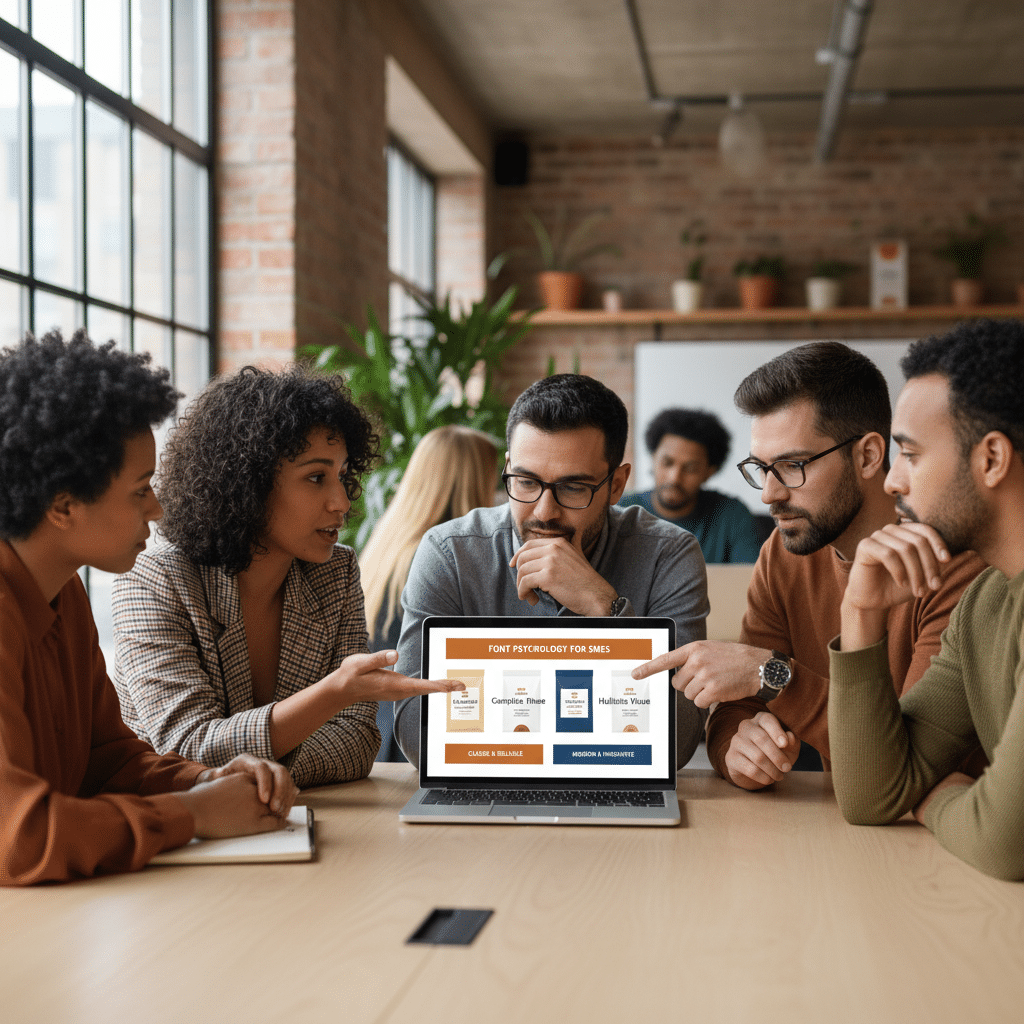
จิตวิทยาฟอนต์: เลือกฟอนต์ยังไงให้แบรนด์ดูน่าเชื่อถือ
การเลือกรูปแบบตัวอักษรหรือฟอนต์สำหรับแบรนด์นั้นมีความสำคัญมากกว่าแค่ความสวยงาม เพราะมันคือเครื่องมือสื่อสารที่ทรงพลังซึ่งทำงานในระดับจิตใต้สำนึกของลูกค้า ศาสตร์ที่ศึกษาเกี่ยวกับเรื่องนี้เรียกว่า จิตวิทยาฟอนต์: เลือกฟอนต์ยังไงให้แบรนด์ดูน่าเชื่อถือ ซึ่งเป็นแนวทางที่ช่วยให้ธุรกิจ โดยเฉพาะกลุ่ม SME สามารถสร้างภาพลักษณ์ที่แข็งแกร่งและน่าไว้วางใจผ่านการออกแบบอัตลักษณ์ของแบรนด์ เช่น โลโก้ ฉลากสินค้า หรือสื่อส่งเสริมการขายต่างๆ
ภาพรวมของจิตวิทยาฟอนต์
- จิตวิทยาฟอนต์ (Font Psychology) คือการศึกษาว่ารูปแบบตัวอักษรที่แตกต่างกันส่งผลต่อการรับรู้ อารมณ์ และพฤติกรรมของมนุษย์อย่างไร
- ฟอนต์ประเภท Serif (มีเชิง/มีหัว) มักสื่อถึงความดั้งเดิม ความน่าเชื่อถือ และความมั่นคง เหมาะสำหรับแบรนด์ที่ต้องการภาพลักษณ์ที่จริงจังและเป็นทางการ
- ฟอนต์ประเภท Sans-serif (ไม่มีเชิง/ไม่มีหัว) ให้ความรู้สึกทันสมัย เรียบง่าย และเข้าถึงง่าย เหมาะสำหรับแบรนด์ดิจิทัลและธุรกิจที่ต้องการสื่อสารความมั่นใจและเป็นมิตร
- การเลือกฟอนต์ที่เหมาะสมต้องคำนึงถึงบุคลิกของแบรนด์ กลุ่มเป้าหมาย และความสอดคล้องกับองค์ประกอบอื่นๆ เพื่อสร้างภาพลักษณ์ที่น่าเชื่อถือและเป็นที่จดจำ
- ความสม่ำเสมอในการใช้ฟอนต์ในทุกช่องทางการสื่อสารเป็นกุญแจสำคัญในการสร้างแบรนด์ที่แข็งแกร่งและน่าไว้วางใจ
ทำความเข้าใจ จิตวิทยาฟอนต์ คืออะไร?
จิตวิทยาฟอนต์ หรือ Font Psychology คือศาสตร์แขนงหนึ่งที่ศึกษาความสัมพันธ์ระหว่างลักษณะทางกายภาพของตัวอักษร (Typography) กับการตอบสนองทางอารมณ์และการรับรู้ของมนุษย์ ฟอนต์แต่ละแบบมี “บุคลิก” ที่แตกต่างกัน ซึ่งสามารถกระตุ้นความรู้สึกและความคิดที่หลากหลายในจิตใต้สำนึกของผู้ชมได้ทันทีที่มองเห็น ไม่ว่าจะเป็นความรู้สึกมั่นคง, ความทันสมัย, ความหรูหรา, หรือความเป็นมิตร สิ่งเหล่านี้เกิดขึ้นโดยอัตโนมัติและส่งผลโดยตรงต่อภาพลักษณ์ของแบรนด์
เมื่อลูกค้าเห็นฟอนต์ที่แบรนด์เลือกใช้ สมองจะประมวลผลและสร้างการเชื่อมโยงกับประสบการณ์หรือแนวคิดที่มีอยู่เดิม ตัวอย่างเช่น ฟอนต์ที่มีลักษณะคล้ายลายมือเขียนอาจทำให้รู้สึกถึงความเป็นส่วนตัวและความใส่ใจ ในขณะที่ฟอนต์ตัวหนาและแข็งแรงอาจสื่อถึงความกล้าหาญและความมั่นคง ดังนั้น การทำความเข้าใจในศาสตร์นี้จึงเป็นสิ่งจำเป็นสำหรับผู้ประกอบการและนักออกแบบที่ต้องการสร้างการสื่อสารที่มีประสิทธิภาพและตรงจุด
ฟอนต์ไม่ใช่แค่ตัวอักษร แต่คือ ‘เสียง’ ที่แบรนด์ใช้สื่อสารโดยไม่ต้องเอ่ยคำพูด มันสามารถกำหนดโทนและสร้างความประทับใจแรกพบที่ทรงพลังได้ในเสี้ยววินาที
ความสำคัญของฟอนต์ต่อการสร้างแบรนด์
ในโลกธุรกิจที่มีการแข่งขันสูง การสร้างความน่าเชื่อถือ (Trustworthiness) คือหัวใจสำคัญสู่ความสำเร็จ ฟอนต์มีบทบาทสำคัญอย่างยิ่งในการสร้างความไว้วางใจนี้ตั้งแต่แรกเห็น โดยเฉพาะอย่างยิ่งในธุรกิจที่ต้องการความมั่นคงสูง เช่น ธุรกิจการเงิน, บริการด้านสุขภาพ, หรือกฎหมาย การเลือกใช้ฟอนต์ที่ไม่เหมาะสมอาจสร้างความรู้สึกไม่เป็นมืออาชีพ, ไม่น่าไว้วางใจ และทำให้ลูกค้าเกิดความลังเลใจได้
ก่อนที่จะตัดสินใจเลือกฟอนต์ใดๆ แบรนด์ควรกำหนด “บุคลิก” ของตนเองให้ชัดเจนเสียก่อน เช่น แบรนด์ต้องการถูกมองว่าเป็นแบรนด์ที่จริงจังและน่าเชื่อถือ หรือเป็นแบรนด์ที่สนุกสนานและเป็นมิตร? เมื่อมีทิศทางที่ชัดเจนแล้ว การเลือกฟอนต์ที่สอดคล้องกับบุคลิกนั้นจะช่วยควบคุมการรับรู้ของลูกค้าและสร้างภาพลักษณ์ที่แข็งแกร่งและเป็นเอกภาพได้ ฟอนต์ที่เลือกอย่างมีกลยุทธ์จะกลายเป็นสินทรัพย์ที่สำคัญในการออกแบบโลโก้, บรรจุภัณฑ์, เว็บไซต์ และสื่อการตลาดทุกชนิด
หลักการสำคัญในการเลือกฟอนต์เพื่อสร้างความน่าเชื่อถือ
การเลือกฟอนต์ที่สามารถเสริมสร้างความน่าเชื่อถือให้กับแบรนด์ได้นั้นต้องอาศัยหลักการพิจารณาหลายประการ เพื่อให้แน่ใจว่าฟอนต์ที่เลือกไม่เพียงแต่สวยงาม แต่ยังสื่อสารคุณค่าและบุคลิกของแบรนด์ได้อย่างถูกต้อง
ความสอดคล้องกับบุคลิกแบรนด์ (Appropriateness)
ฟอนต์ที่เลือกต้องสอดคล้องกับยุคสมัย, บุคลิก, และค่านิยมหลักของแบรนด์ แบรนด์ที่ต้องการสื่อถึงความเป็นดั้งเดิมและความน่าเชื่อถือที่สืบทอดมายาวนาน อาจเลือกใช้ฟอนต์ประเภท Serif ที่ดูคลาสสิก ในทางกลับกัน แบรนด์เทคโนโลยีที่ต้องการสื่อถึงความทันสมัยและนวัตกรรม มักจะเลือกใช้ฟอนต์ Sans-serif ที่ดูสะอาดตาและเรียบง่าย การเลือกฟอนต์ที่ไม่เข้ากับบริบทของธุรกิจอาจสร้างความสับสนและลดทอนความน่าเชื่อถือลงได้
ความชัดเจนและอ่านง่าย (Readability)
นี่คือคุณสมบัติพื้นฐานที่สำคัญที่สุด ฟอนต์ที่น่าเชื่อถือต้องอ่านง่ายและชัดเจนในทุกขนาดและทุกสื่อ ไม่ว่าจะเป็นบนหน้าจอ ดิจิทัลหรือบนสื่อสิ่งพิมพ์ ตัวอักษรที่ไม่ซับซ้อนและมีช่องไฟที่เหมาะสมจะช่วยให้ผู้อ่านรับสารได้อย่างรวดเร็วและไม่รู้สึกติดขัด การเลือกฟอนต์ที่อ่านยากอาจทำให้ลูกค้ารู้สึกหงุดหงิดและมองว่าแบรนด์ขาดความเป็นมืออาชีพ ซึ่งส่งผลลบต่อความไว้วางใจโดยตรง
เอกลักษณ์และความโดดเด่น (Uniqueness)
ในขณะที่ต้องอ่านง่าย ฟอนต์ก็ควรมีเอกลักษณ์ที่ช่วยให้แบรนด์เป็นที่จดจำได้ การเลือกใช้ฟอนต์ที่แตกต่างแต่ไม่แปลกจนเกินไปจะช่วยสร้างความโดดเด่นท่ามกลางคู่แข่ง อย่างไรก็ตาม ควรหลีกเลี่ยงฟอนต์ที่ถูกใช้งานอย่างแพร่หลายจนกลายเป็นฟอนต์พื้นฐานทั่วไป เพราะอาจทำให้แบรนด์ดูไม่มีเอกลักษณ์และไม่น่าจดจำ การสร้างสมดุลระหว่างความเป็นเอกลักษณ์และความคุ้นเคยคือสิ่งสำคัญ